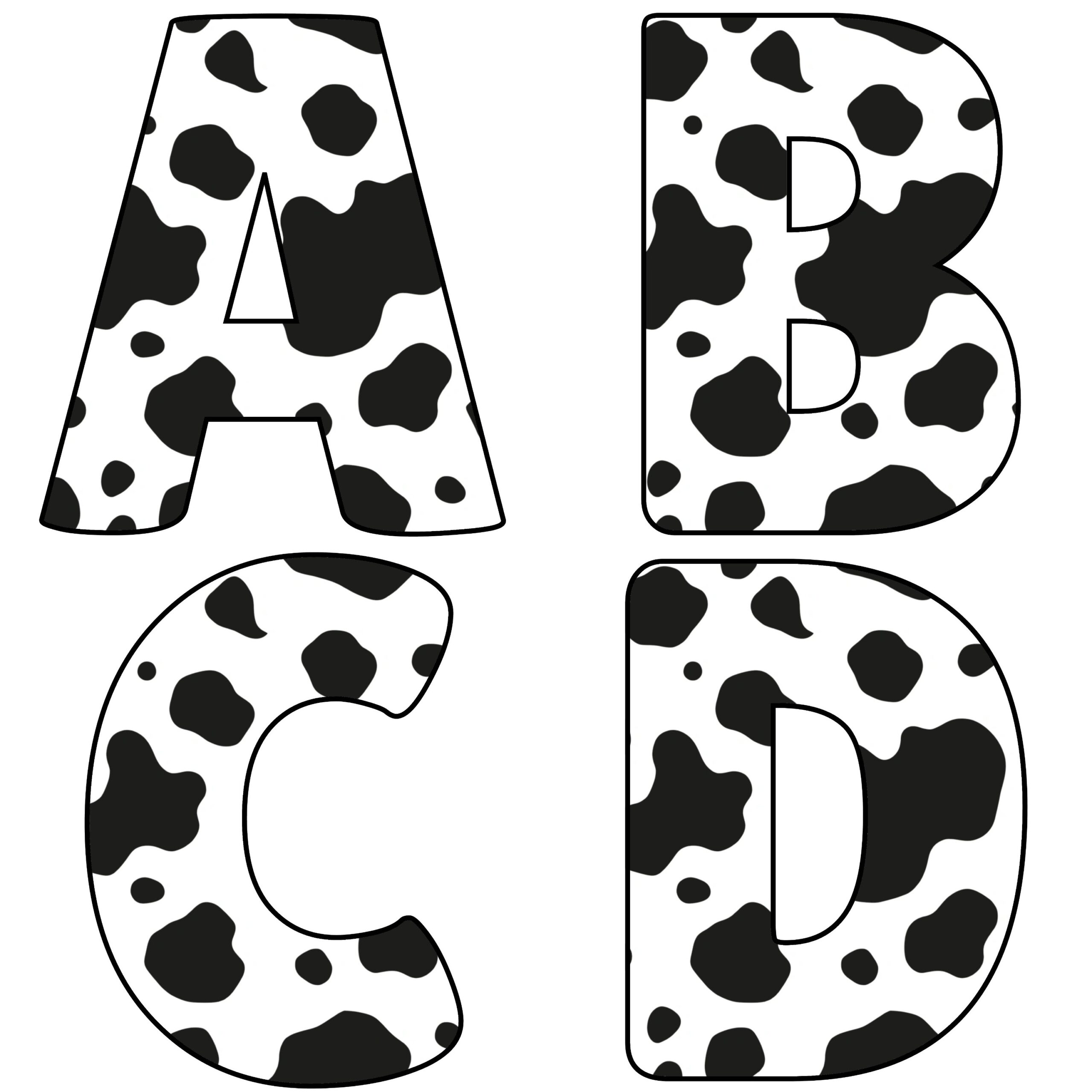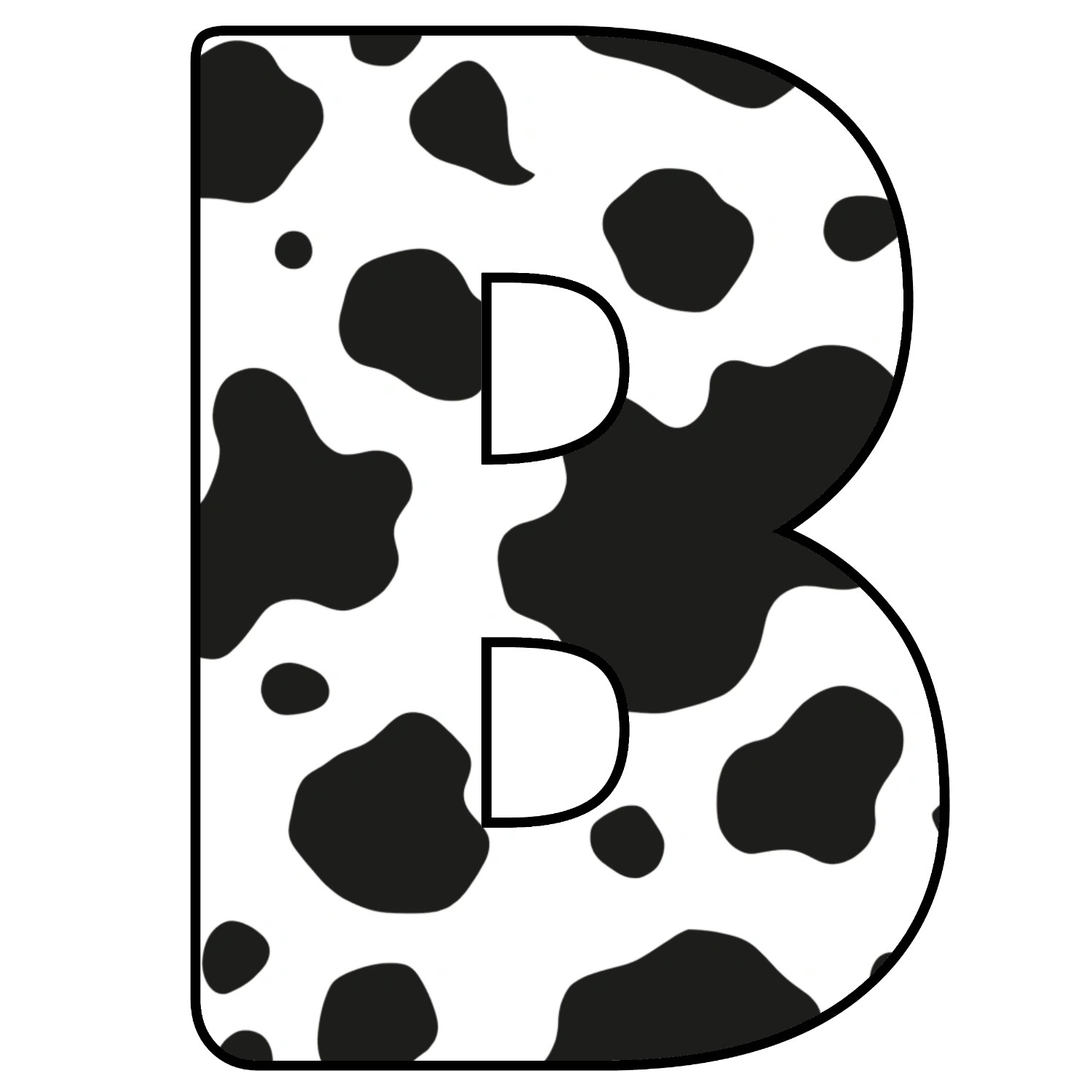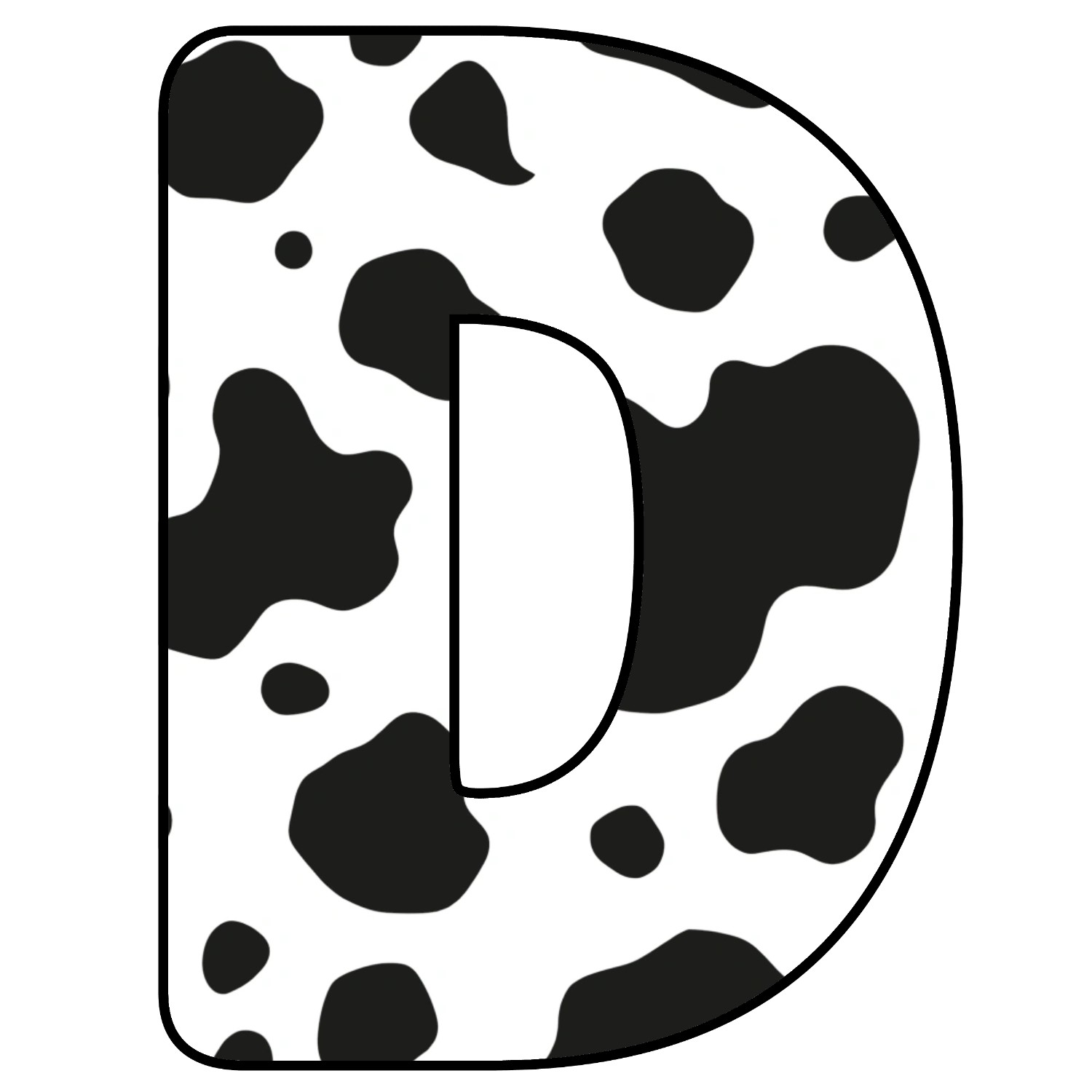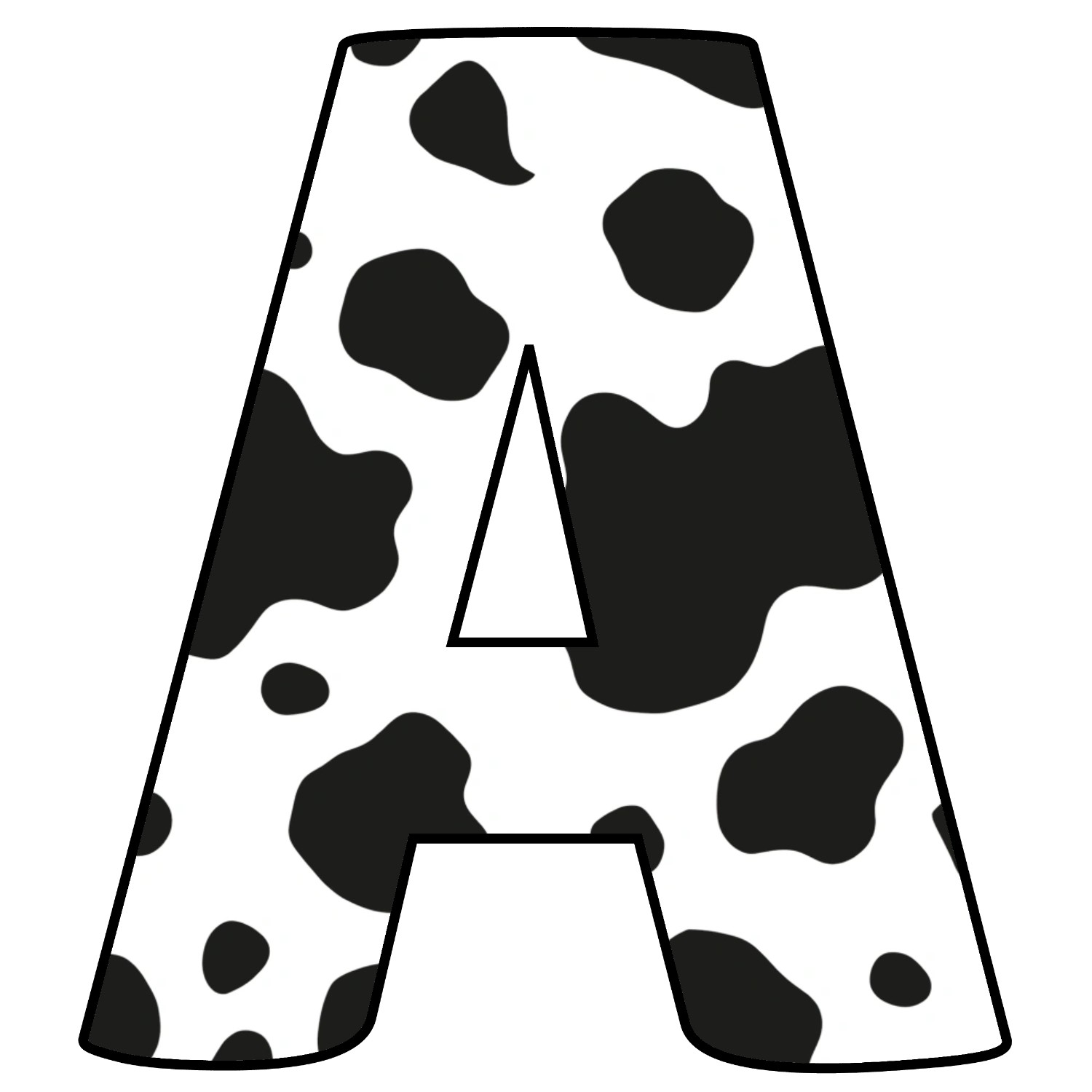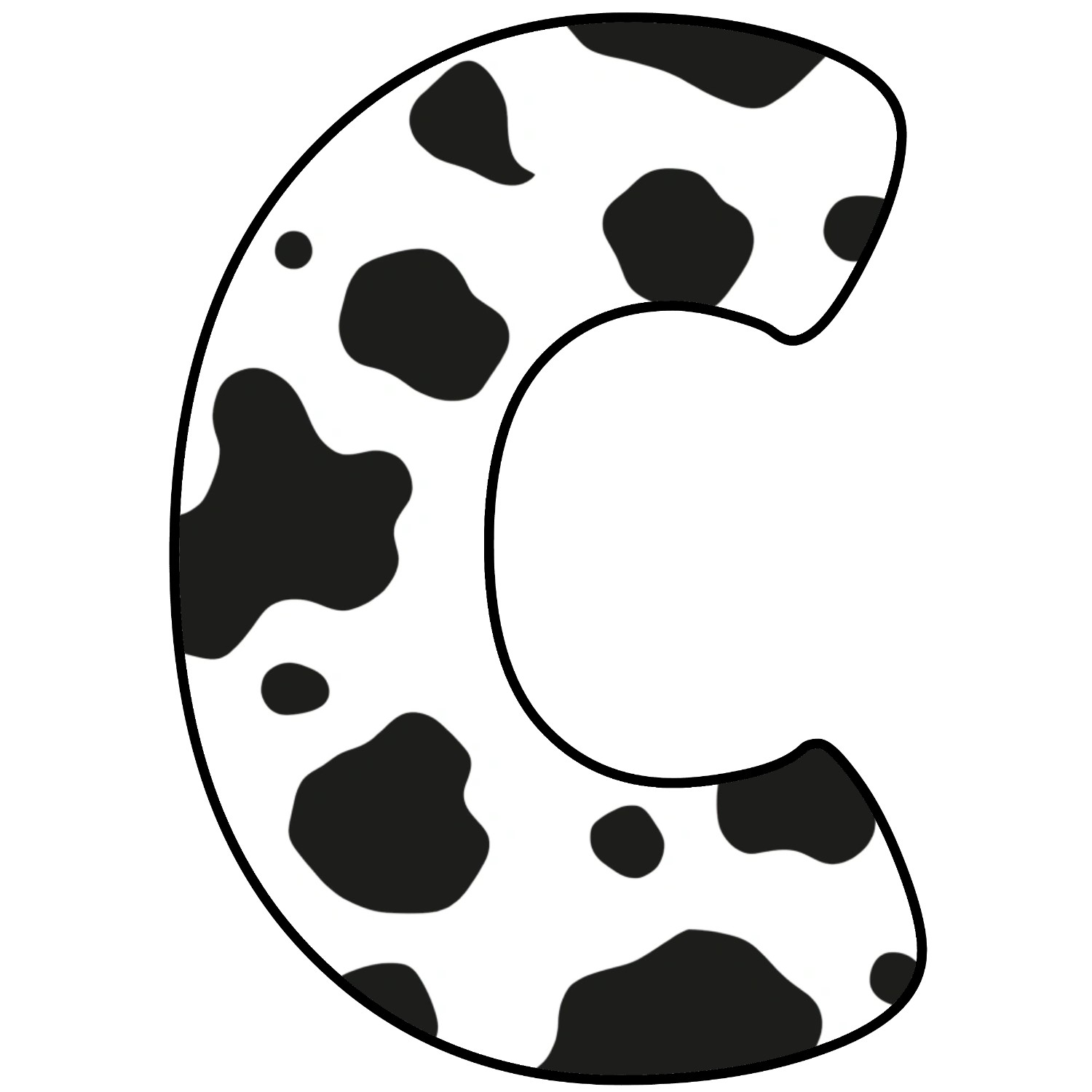
Imprimí, decorá y personalizá tus fiestas y proyectos con este increíble Alfabetos de Pieles De Animales – Vaca. En FontPic, transformamos cualquier fondo que te guste en un abecedario completo, listo para usar. ¿Tenés una imagen o un diseño propio? Subilo a nuestra herramienta y creá tus propias letras personalizadas en un instante. ¡La creatividad no tiene límites!
🔍Cada letra ha sido diseñada para que la impresión sea perfecta. Son ideales para crear guirnaldas con nombres, carteles de feliz cumpleaños, decorar salones de clase o cualquier proyecto creativo que tengas en mente. Gracias a su formato cuadrado y alta resolución, recortarlas es muy fácil y el resultado siempre es profesional.